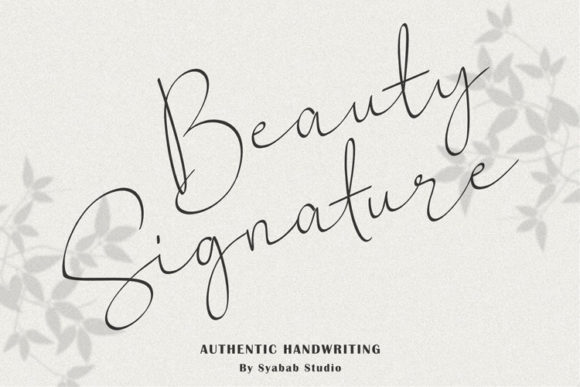
Creativefabrica Beauty Signature Font
[Creativefabrica] Beauty Signature Font
Beauty Signature - тонкий и модный шрифт.
Он имеет стильный, элегантный и современный вид, который может быть использован для логотипов, брендинга, приглашений, канцелярских принадлежностей, свадебных конструкций, сообщений в социальных сетях, и многое другое!